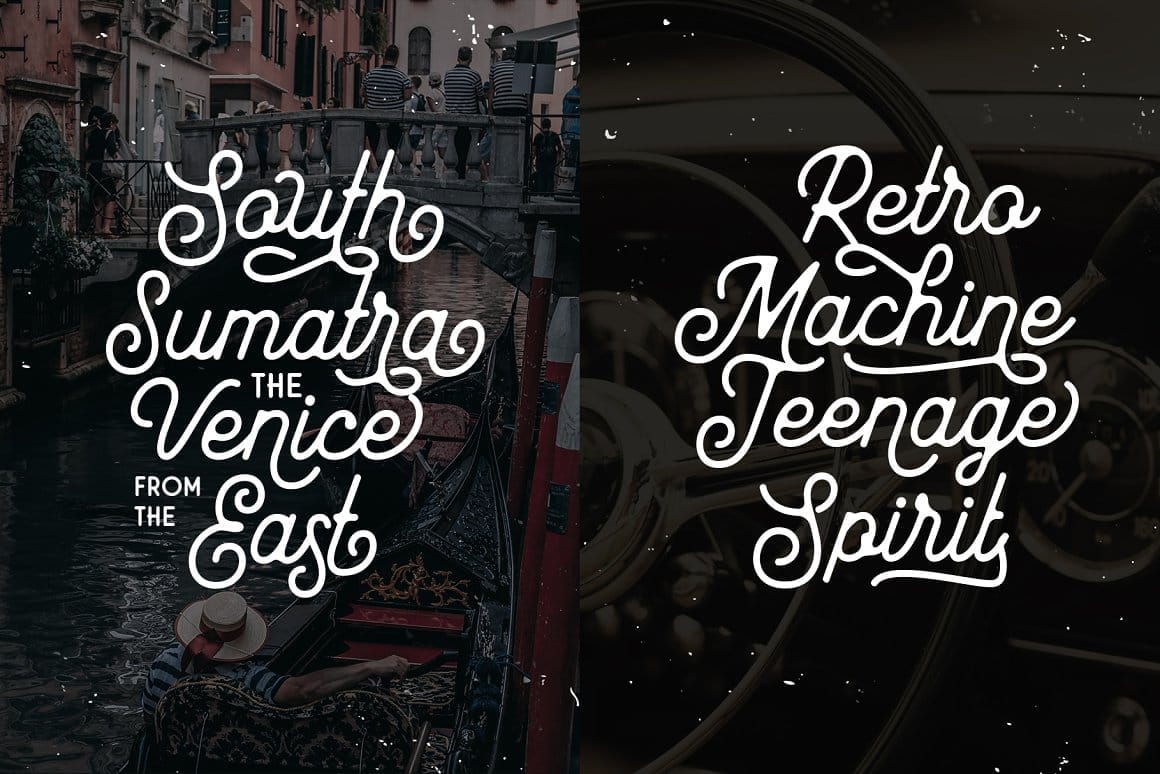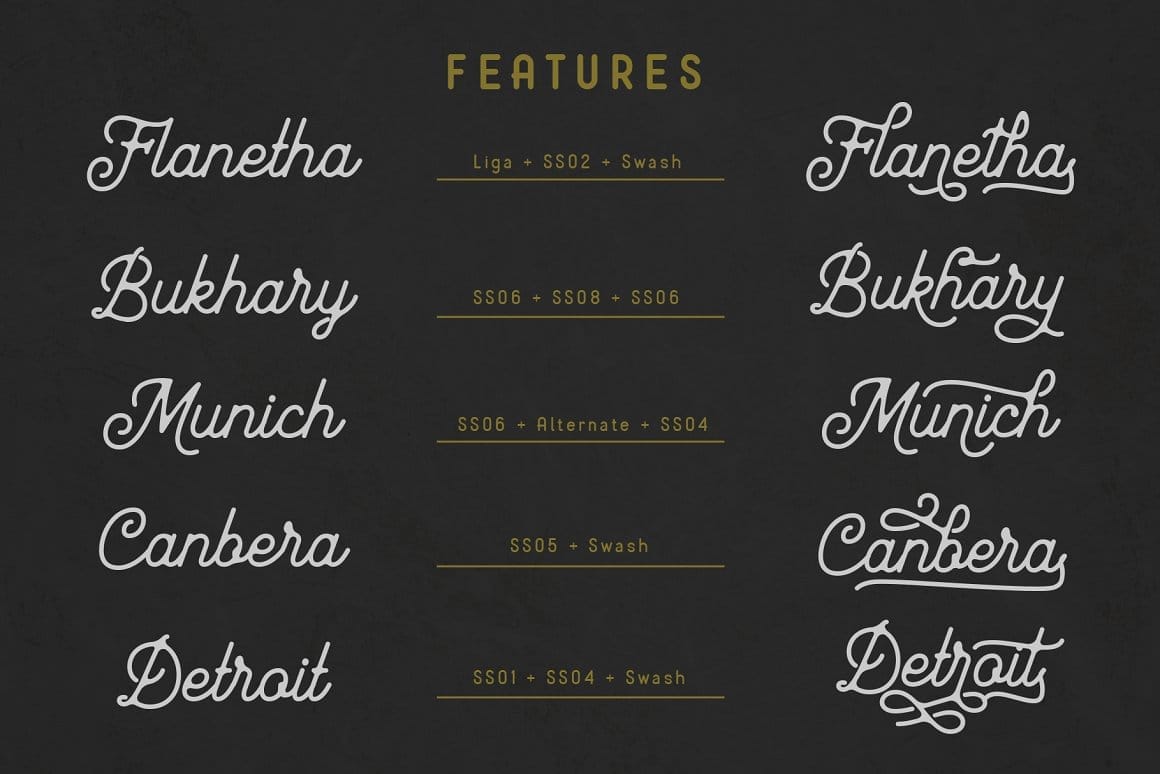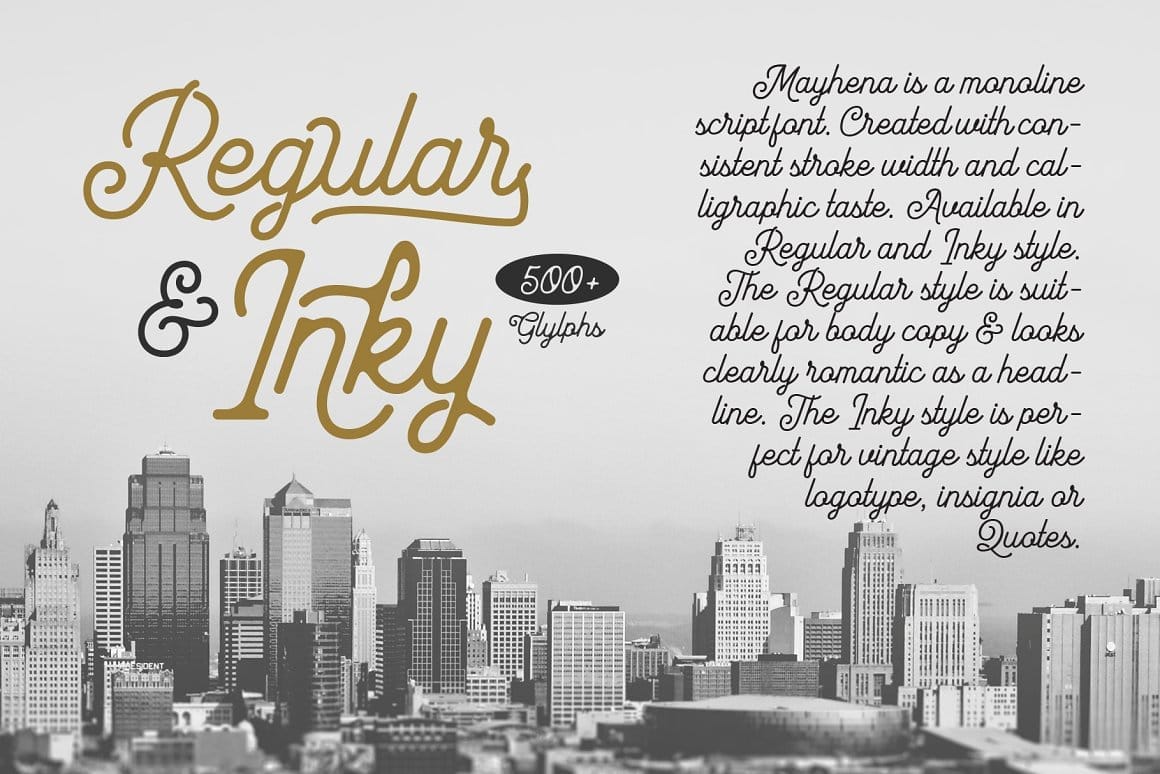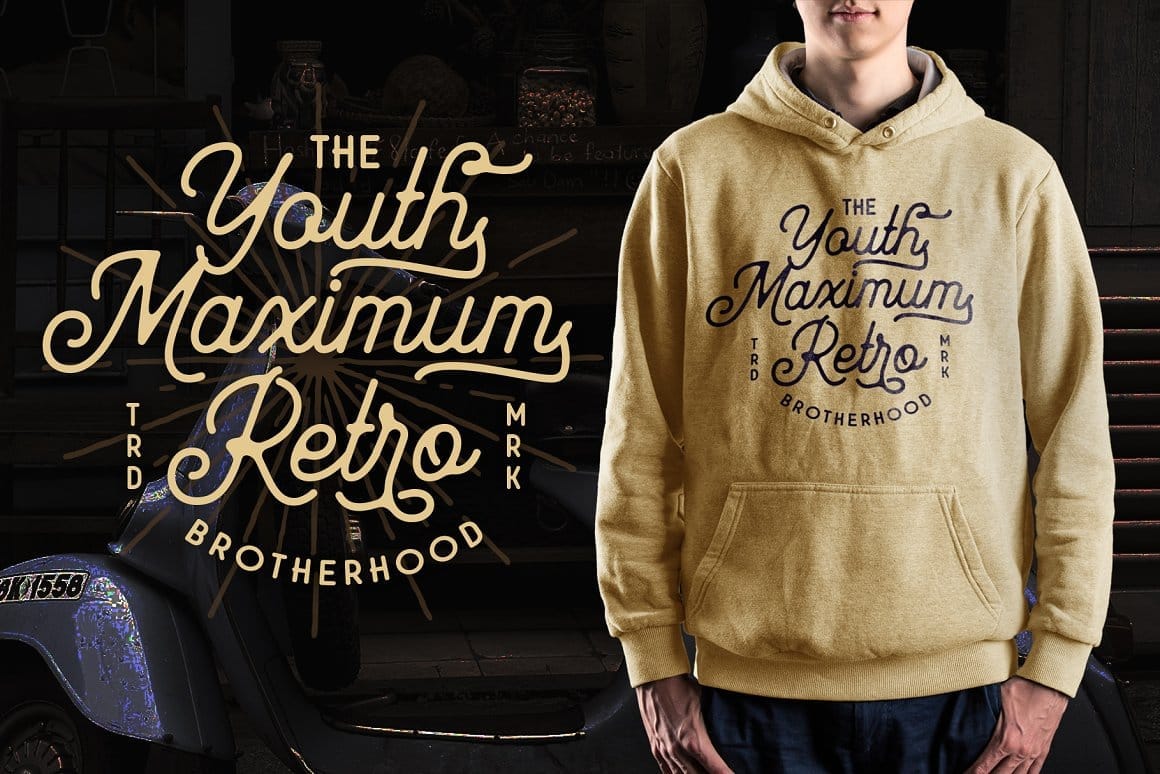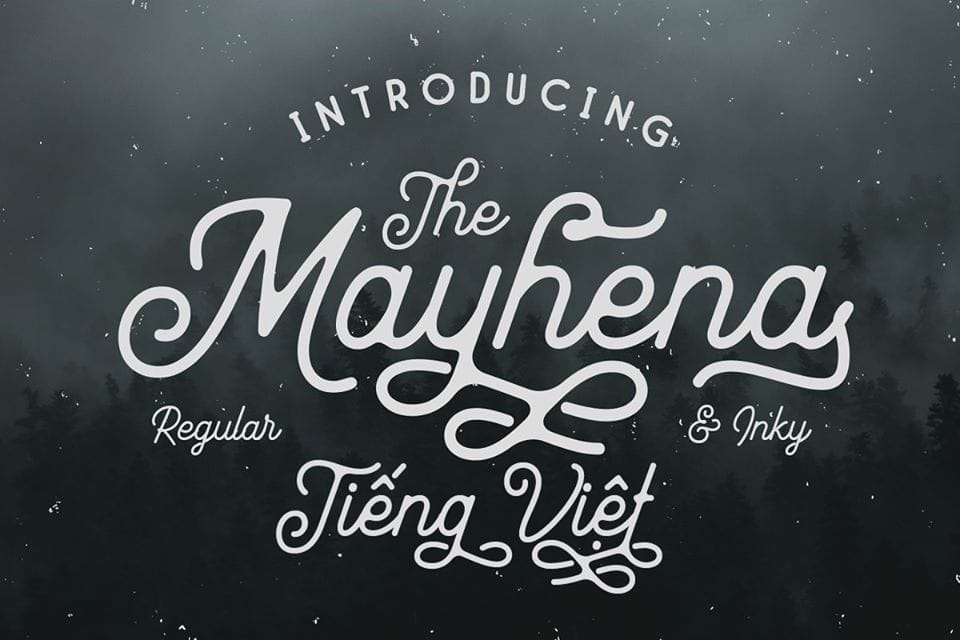
Giới thiệu Mayhena Monoline Font
Các phông chữ monoline được kết nối với vẻ cổ điển. Đi kèm theo phong cách Regular và Inky mà bạn có thể sử dụng để tạo kiểu chữ cổ điển đẹp cho bất kỳ dự án nào của bạn như áo phông, hàng hóa, logo, phù hiệu, nhãn hiệu, áp phích, tạp chí, bao bì, báo giá và nhiều hơn nữa.
Phông chữ Mayhena hoàn chỉnh với các kiểu thay thế và bộ từ 01 đến 08 mà bạn có thể thực hiện nhiều biến thể của kiểu chữ như swash dài, swash ngắn, đuôi trang trí, nét cuối và nhiều hơn nữa. Hỗ trợ 27 ngôn ngữ với hơn 500 glyphs!
- Uppercase
- Lowercase
- Symbols
- Numbers
- Accents
- Ligatures
Alternates - SS01 – SS08